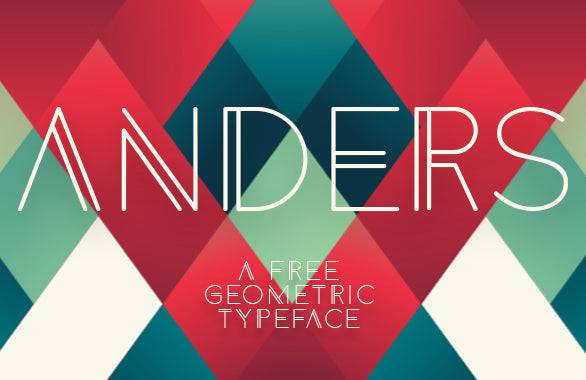
Fonte Anders para projetos de artesanato, logotipos e impressão.
Anders é uma tipografia moderna sem serifa com uma estrutura geométrica e minimalista, ideal para identidade visual limpa, sistemas de logotipos e trabalhos impressos de alto impacto. Suas linhas nítidas e ritmo estruturado favorecem tanto a simplicidade quanto a sofisticação em composições de design.
Esta fonte é ideal para designers gráficos, criadores e especialistas em impressão que buscam criar layouts modernos com clareza e uma estética arrojada. Anders é especialmente eficaz em editoriais, embalagens e sistemas de identidade visual.
Sua versatilidade em plataformas impressas e digitais permite que funcione perfeitamente em diversos meios, desde etiquetas de produtos a banners da web e material promocional.
- Design moderno, limpo e altamente legível.
- Ideal para projetos de design focados na marca.
- Bordas geométricas elegantes para um visual profissional.
P: Que tipo de fonte é a Anders?
A: Anders é uma fonte geométrica sem serifa com uma estrutura minimalista moderna, excelente para impressão e identidade visual.
A: Com certeza. O Anders foi projetado com linhas limpas e escalabilidade, tornando-o adequado para todos os formatos de impressão profissionais.
| Estilo da fonte | fonte geométrica moderna sem serifa | Tipografia limpa neo-grotesca | Fonte minimalista moderna e fina |